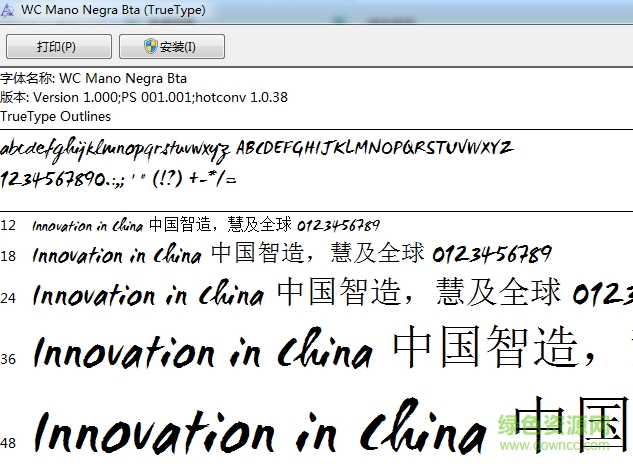
WC Mano Negra Bta字體是一款超好用的英文字體,字體的線條優(yōu)美,十分飄逸的書寫方式,讓用戶視覺體驗(yàn)爽到不行,有喜歡這款字體的朋友就趕快來綠色資源網(wǎng)下載使用吧!
WC Mano Negra Bta字體是一款英文字體,該字體獨(dú)有的線條,讓用戶能夠輕松記住它,有需要的朋友就趕快來綠色資源網(wǎng)下載吧!